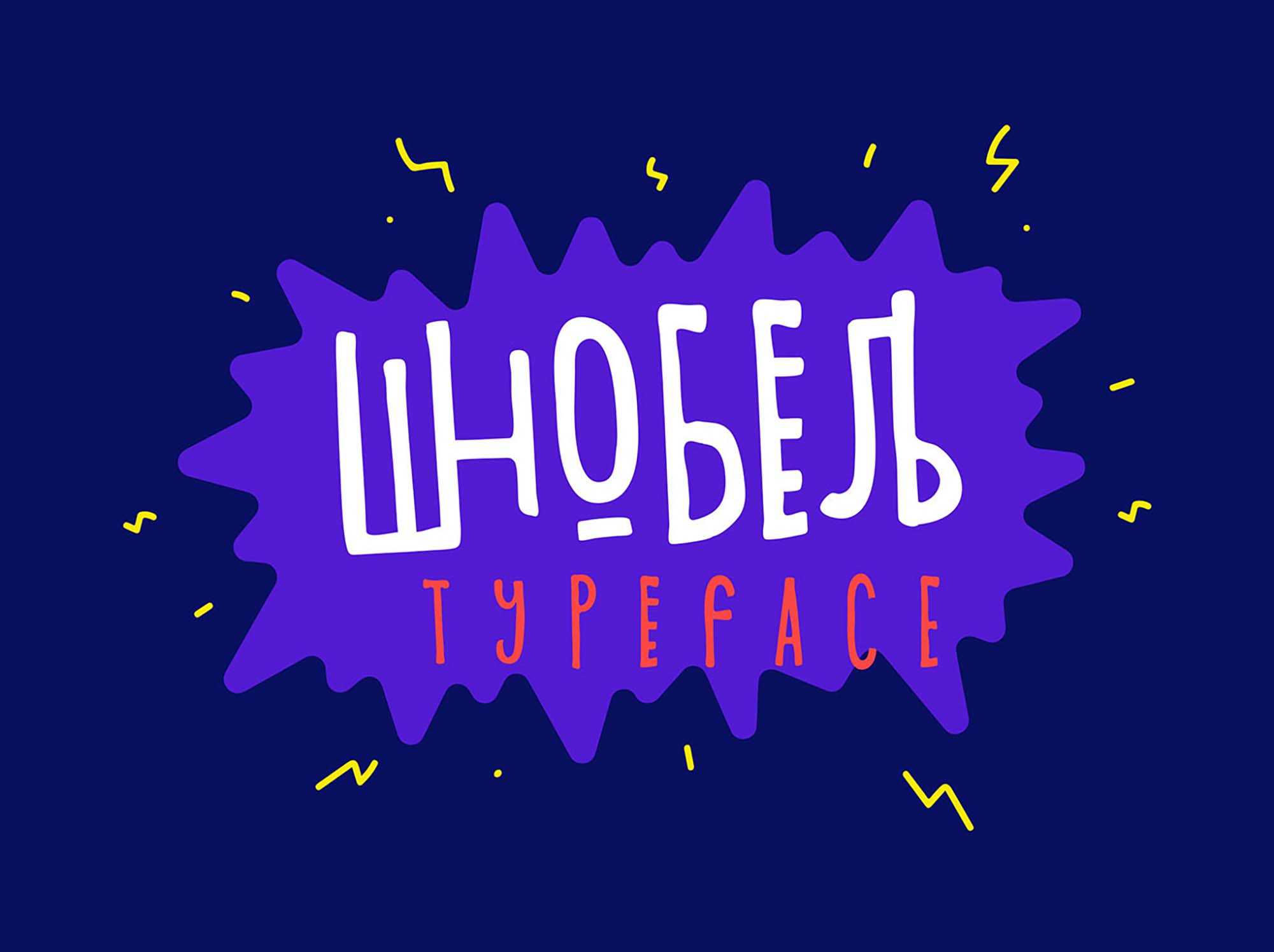
Free Shnobel Display Typeface – Download Grátis
A Shnobel Display Typeface é uma fonte de exibição que criará um impacto imediato em qualquer projeto que você esteja realizando. Se você está procurando algo que chame atenção, algo que se destaca, então você chegou ao lugar certo. Este novo recurso gráfico, com sua rara combinação de letras e cores, oferece uma opção única para expressar sua personalidade e suas ideias de maneira inovadora e divertida. Estamos extremamente entusiasmados para compartilhar esta fonte de exibição de Shnobel com você, sabendo que você vai apreciar a sua criatividade única.